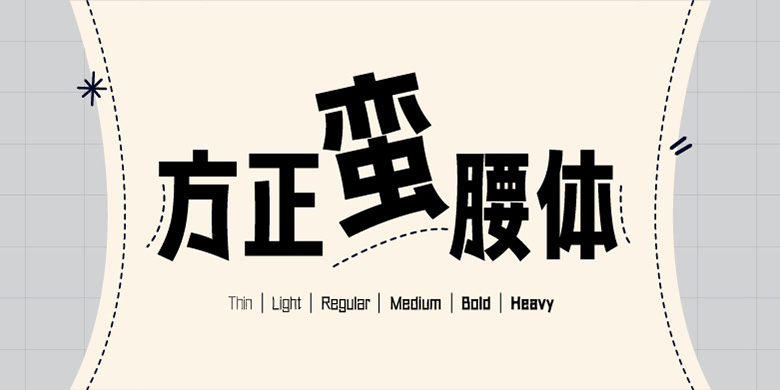
方正蛮腰体家族
字体品牌: 方正字库 设计师:蒋志龙 字体分类:创意字体 字体属性:精品字 字符集:大陆简体(GB2312-80) 发布时间: 2023
这是一款源自女性形体曲线之美的灵感而设计出纤细修长的字体,以上、中、下笔画平直和左右笔画收腰而呈现出束腰、苗条、高挑的字形特征,结字简明素静,笔画纤细简练,既呈现出黑体的干劲韧性,又展现出女性典雅聪颖和自信的气质和姿态,适用于女性品牌的视觉设计。